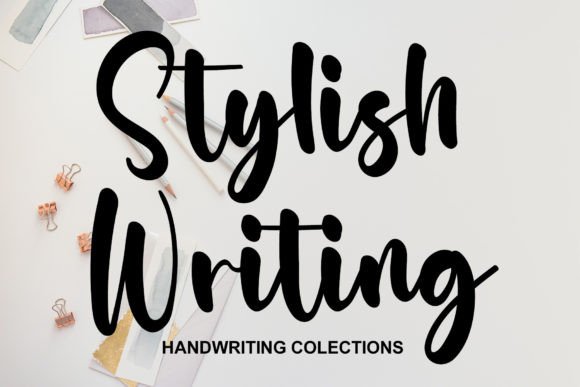
Stylish Writing
Ulasan Lengkap Stylish Writing – Font Manuscrit Élégant et Romantique
Vous cherchez une police qui allie élégance, joie et une touche de romantisme ? Ne cherchez plus : Stylish Writing est la réponse à toutes vos attentes créatives. Ce script manuscrit captivant se démarque par son charme irrésistible et sa capacité à sublimer aussi bien les projets personnels que professionnels.
Pourquoi choisir Stylish Writing ?
- Design raffiné : chaque caractère possède des courbes fluides et des terminaisons délicates qui apportent une note sophistiquée à vos créations.
- Polyvalence exceptionnelle : idéal pour les invitations, les cartes de vœux, les logos, les sites web, les affiches et même les présentations PowerPoint.
- Impact émotionnel : son style manuscrit ajoute une dimension personnelle et chaleureuse, créant instantanément un lien émotionnel avec votre audience.
Expérience utilisateur – Ce que vous ressentirez
En travaillant avec Stylish Writing, chaque trait semble danser sur la page. Vous ressentirez immédiatement un sentiment de légèreté et de plaisir, comme si votre texte prenait vie. Cette police transforme un simple message en une véritable œuvre d’art, tout en conservant une lisibilité optimale.
Cas d'utilisation recommandés
- Invitations de mariage ou de fiançailles – pour un effet romantique inoubliable.
- Branding de petites entreprises artisanales – ajoutez une touche d’authenticité.
- Templates de réseaux sociaux – créez des posts qui se démarquent dans le fil d’actualité.
- Couvertures de livres et titres de chapitres – donnez une allure littéraire à vos écrits.
- Packaging de produits de luxe – renforcez le positionnement haut de gamme.
Conclusion – Le choix évident pour vos projets créatifs
Stylish Writing n’est pas seulement une police, c’est une véritable expérience visuelle qui marie élégance et fantaisie. Que vous soyez designer, marketeur ou passionné de création, cette police vous aidera à transmettre votre message avec une signature unique et mémorable. N’attendez plus, téléchargez Stylish Writing et laissez chaque trait raconter votre histoire.